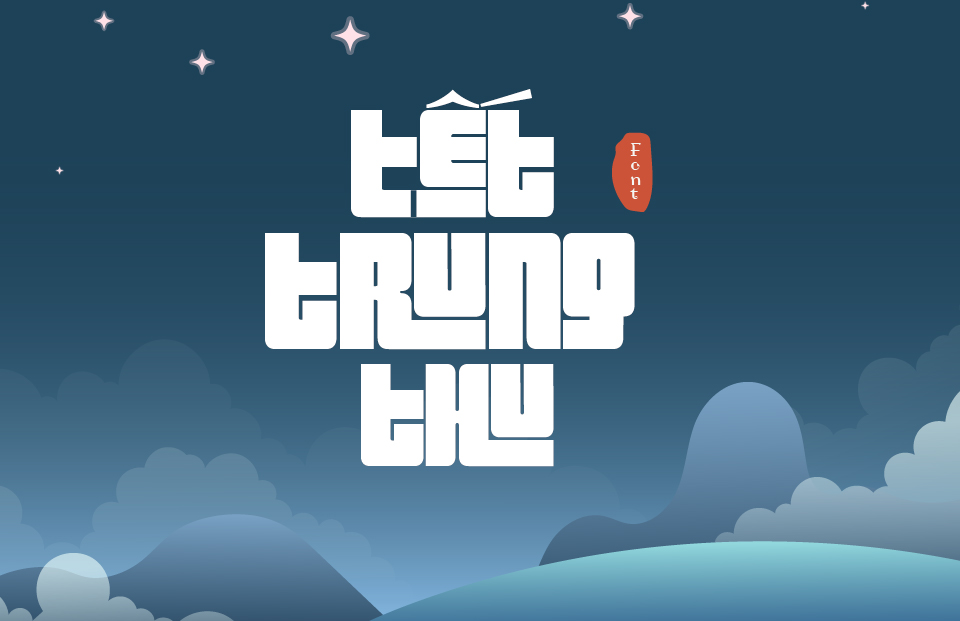
Font Việt hóa LNTH Pincoya Black – Font trung thu
Font Việt hóa LNTH Pincoya Black – Font trung thu – Lựa chọn hoàn hảo cho thiết kế tết đoàn viên
Trong thế giới thiết kế đồ họa, việc lựa chọn một bộ Font Miễn Phí chất lượng luôn là ưu tiên hàng đầu của các nhà sáng tạo. Đặc biệt khi mùa lễ hội đang đến gần, nhu cầu tìm kiếm những kiểu chữ độc đáo để làm nổi bật thông điệp truyền thông ngày càng tăng cao. Font Việt hóa LNTH Pincoya Black – Font trung thu chính là một trong những siêu phẩm được săn đón nhất hiện nay. Với phong cách đậm chất nghệ thuật, bộ font này không chỉ mang lại vẻ đẹp thẩm mỹ mà còn giúp truyền tải trọn vẹn tinh thần ấm áp của ngày tết đoàn viên. Bài viết sau đây sẽ giúp bạn hiểu rõ lý do vì sao bộ chữ này lại trở thành xu hướng hàng đầu trong cộng đồng thiết kế Việt Nam.
Đặc điểm nổi bật của Font Việt hóa LNTH Pincoya Black – Font trung thu
Phong cách thiết kế dày dặn và mạnh mẽ
LNTH Pincoya Black gây ấn tượng mạnh mẽ ngay từ cái nhìn đầu tiên nhờ độ dày (weight) cực lớn. Các đường nét được bo tròn tinh tế nhưng vẫn giữ được sự chắc chắn, tạo nên một tổng thể hài hòa và đầy sức sống. Đây là kiểu chữ lý tưởng để sử dụng cho các tiêu đề lớn, banner quảng cáo hoặc các ấn phẩm cần sự chú ý ngay lập tức. Sự tương phản giữa các nét thanh và nét đậm trong bộ font này giúp tạo ra nhịp điệu thị giác thú vị, khiến nội dung của bạn trở nên sinh động và chuyên nghiệp hơn bao giờ hết.
Khả năng tương thích và tối ưu hóa tiếng Việt Font Việt hóa LNTH Pincoya Black – Font trung thu
Một trong những điểm cộng lớn nhất của Font Việt hóa LNTH Pincoya Black – Font trung thu chính là bộ dấu tiếng Việt được trau chuốt tỉ mỉ. Việc Việt hóa không chỉ đơn thuần là thêm dấu mà còn là sự căn chỉnh sao cho các dấu thanh không làm phá vỡ cấu trúc ban đầu của chữ cái. Điều này giúp các nhà thiết kế tại Việt Nam yên tâm sử dụng trong các dự án chuyên nghiệp mà không lo lỗi font hay mất thẩm mỹ. Bộ chữ này hỗ trợ đầy đủ các ký tự đặc biệt, giúp việc soạn thảo nội dung trở nên mượt mà và đồng nhất trên mọi nền tảng đồ họa hiện nay.
Ứng dụng Font Việt hóa LNTH Pincoya Black – Font trung thu trong đời sống
Thiết kế bao bì bánh trung thu và thiệp chúc mừng
Đúng như tên gọi của mình, bộ font này cực kỳ phù hợp cho các chủ đề liên quan đến tết thiếu nhi. Bạn có thể sử dụng nó để thiết kế nhãn mác cho các hộp bánh trung thu truyền thống, tạo cảm giác sang trọng nhưng vẫn gần gũi. Ngoài ra, các mẫu thiệp chúc mừng gửi tặng người thân, bạn bè cũng sẽ trở nên ý nghĩa hơn khi sử dụng những nét chữ tròn trịa, biểu trưng cho sự viên mãn của vầng trăng rằm. Sự kết hợp giữa màu đỏ may mắn và màu vàng kim trên nền chữ Pincoya Black chắc chắn sẽ tạo nên một tác phẩm nghệ thuật ấn tượng.
Trang trí sự kiện và backdrop sân khấu
Tại các trường học hay cơ quan, việc tổ chức đêm hội trăng rằm không thể thiếu các tấm backdrop rực rỡ. Font Việt hóa LNTH Pincoya Black – Font trung thu với kích cỡ lớn sẽ giúp các em nhỏ và khách mời dễ dàng quan sát từ xa. Kiểu chữ này mang lại cảm giác vui tươi, hồn nhiên, rất phù hợp với không khí náo nức của trẻ thơ. Bên cạnh đó, các bạn học sinh cũng có thể ứng dụng bộ font này để làm báo tường, trang trí lớp học hoặc thiết kế các trò chơi tương tác trong đêm hội, giúp không gian sinh hoạt chung thêm phần bắt mắt và sáng tạo.